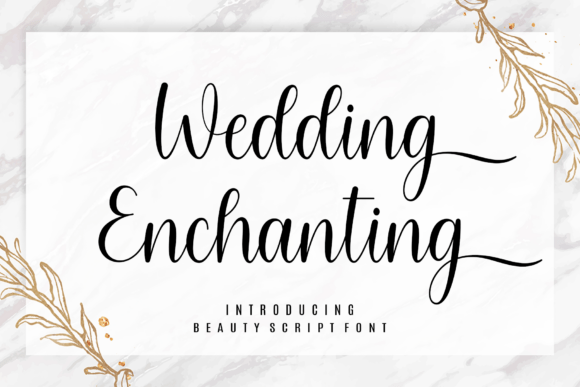
Wedding Enchanting
Wedding Enchanting : L'Élément Décoratif Parfait Pour Votre Jour de Mariage
** **Un Mélange Captivant de Sophistication et de Beauté
**Si vous cherchez un élément décoratif pour ajouter un peu de magie à votre jour de mariage, Wedding Enchanting est la parfaite solution. Cet élégant script font est conçu pour ajouter une touche de romantisme à vos messages chaleureux, tout en évoquant l'éternité et la beauté.
**Les Atouts de Wedding Enchanting
**- **Élévation de la Sophistication** : Wedding Enchanting est un mélange captivant de sophistication et de beauté, infusé dans un script font élégant.
- **Équilibre de l'Elegance** : Ce font parfaît équilibre la délicate élégance avec un style durable et éternel.
- **Radiation de Charme et de Grâce** : Wedding Enchanting rayonne de charme et de grâce, ajoutant un touché de romance à vos messages.
- **Narration de Rêve** : Ce font est conçu pour amplifier les récits d'amour et de célébration éternelle.
Embrassez l'Enchantement de Wedding Enchanting
**N'attendez plus pour ajouter un peu de magie à votre jour de mariage ! Embrassez l'Enchantement de Wedding Enchanting, un font conçu pour vous accompagner dans l'éternité de votre amour.